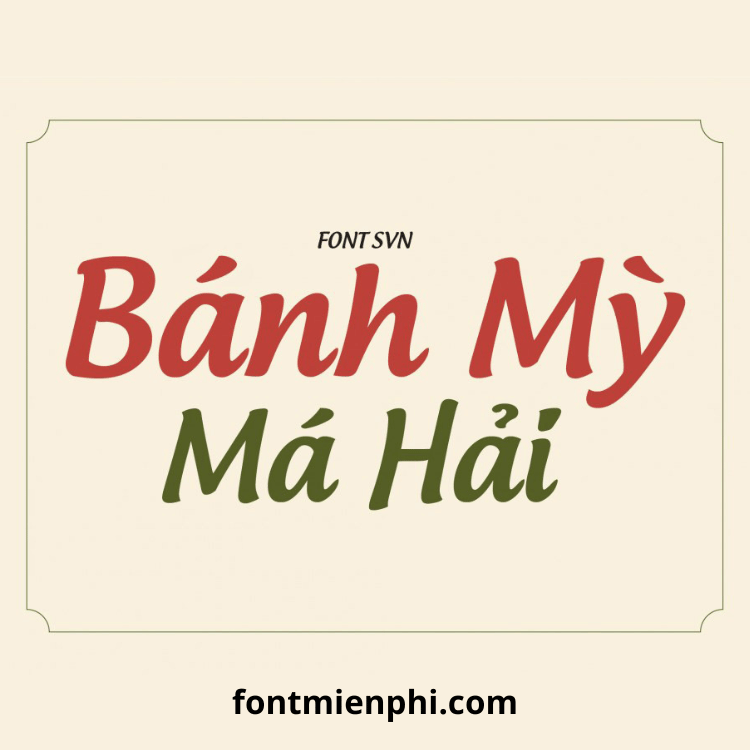
Việt hóa font SVN Androgyne
Giới Thiệu Font SVN Androgyne Việt Hóa
Font SVN Androgyne Việt Hóa là phiên bản được tối ưu hóa cho tiếng Việt, dựa trên font Androgyne gốc với phong cách thanh lịch, hiện đại. Với kiểu chữ mềm mại nhưng không kém phần sang trọng, font này phù hợp cho thiết kế thời trang, tạp chí, nhãn hiệu, và các dự án sáng tạo đòi hỏi sự tinh tế.
✅ Hỗ trợ đầy đủ dấu tiếng Việt – Không lỗi font, đẹp mọi kích thước
Điểm Nổi Bật Của Font SVN Androgyne Việt Hóa
• Phong cách độc đáo: Nét chữ mảnh mai, thanh thoát, phù hợp với thiết kế thời trang, logo cao cấp.
• Đa dạng ứng dụng: Dùng cho in ấn, branding, website, social media, và thiết kế đồ họa.
• Tối ưu hóa tiếng Việt: Đảm bảo rõ ràng, không bị vỡ nét khi sử dụng dấu.
Kết Luận